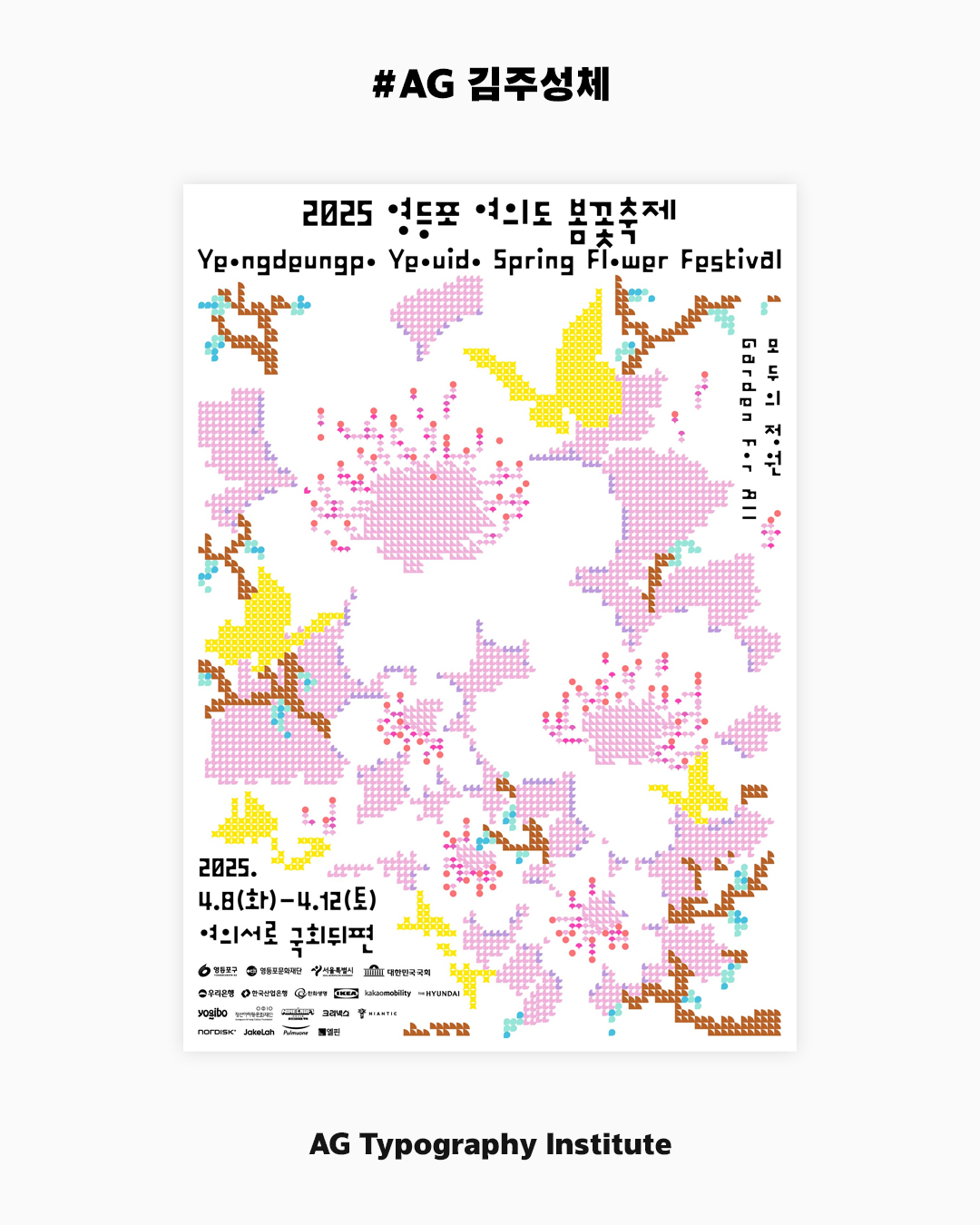
AG 김주성체
AG Kimjoosung
〈AG 김주성체〉는 디자이너 김주성의 탈네모꼴 레터링을 바탕으로 개발한 글꼴이다. 김주성은 가장 기본적인 조형 요소인 점과 선을 감각적으로 활용해 한글 자소를 디자인했다. 〈AG 김주성체〉의 이응은 점 형태이며, 그 외의 닿자는 모듈처럼 획의 수에 따라 크기가 달라지는 가변적인 형태이다. 다양한 너비와 높이의 자소가 조합하여 모임꼴에 따라서도 글자의 높낮이와 자폭도 달라진다. 글자마다 너비와 높이가 다양한만큼 글줄의 리듬감을 유지하면서도 흐름이 안정적일수 있도록 글자 특성에 적합한 탈네모꼴 조합규칙을 만들었다. 한글의 독특한 형태와 어울리도록 라틴 알파벳과 기호활자를 제작하여 〈AG 김주성체〉를 완성했다. 한글 11,172자, 로마자 및 확장 로마자 305자, 그리고 문장 부호를 포함한 기호 활자 705자를 지원한다.